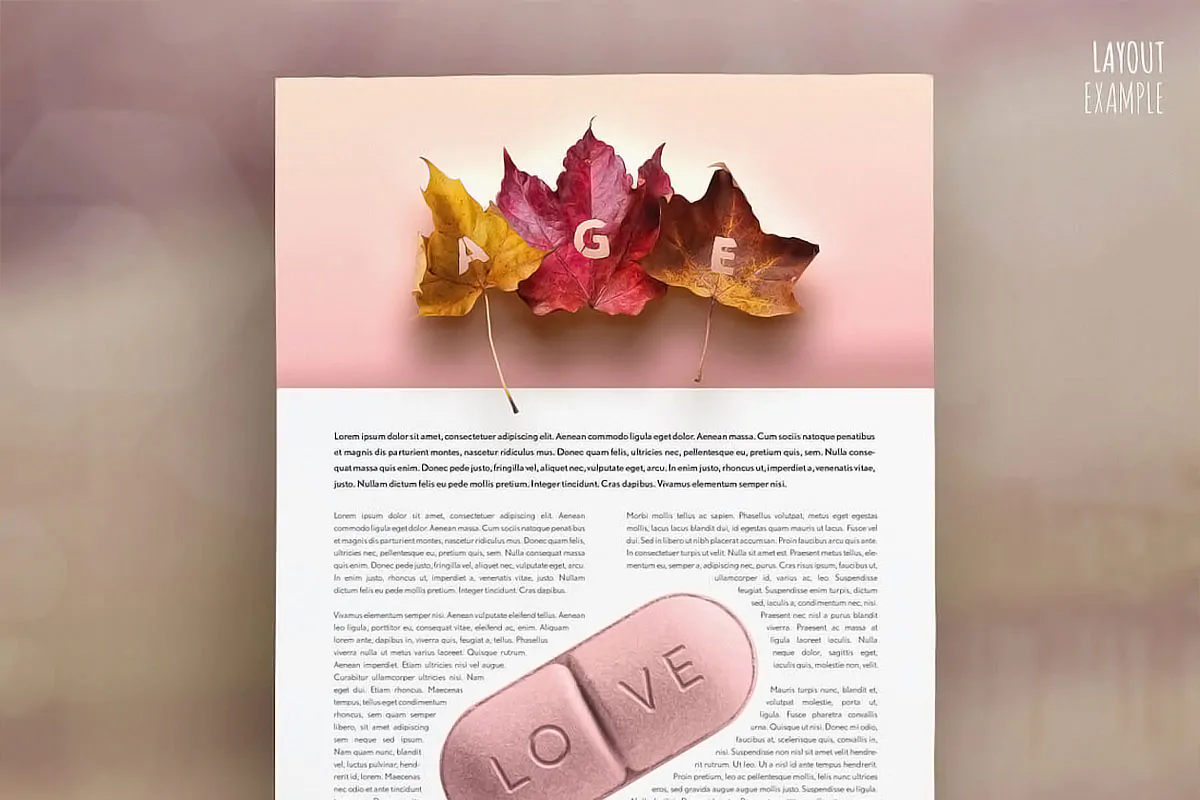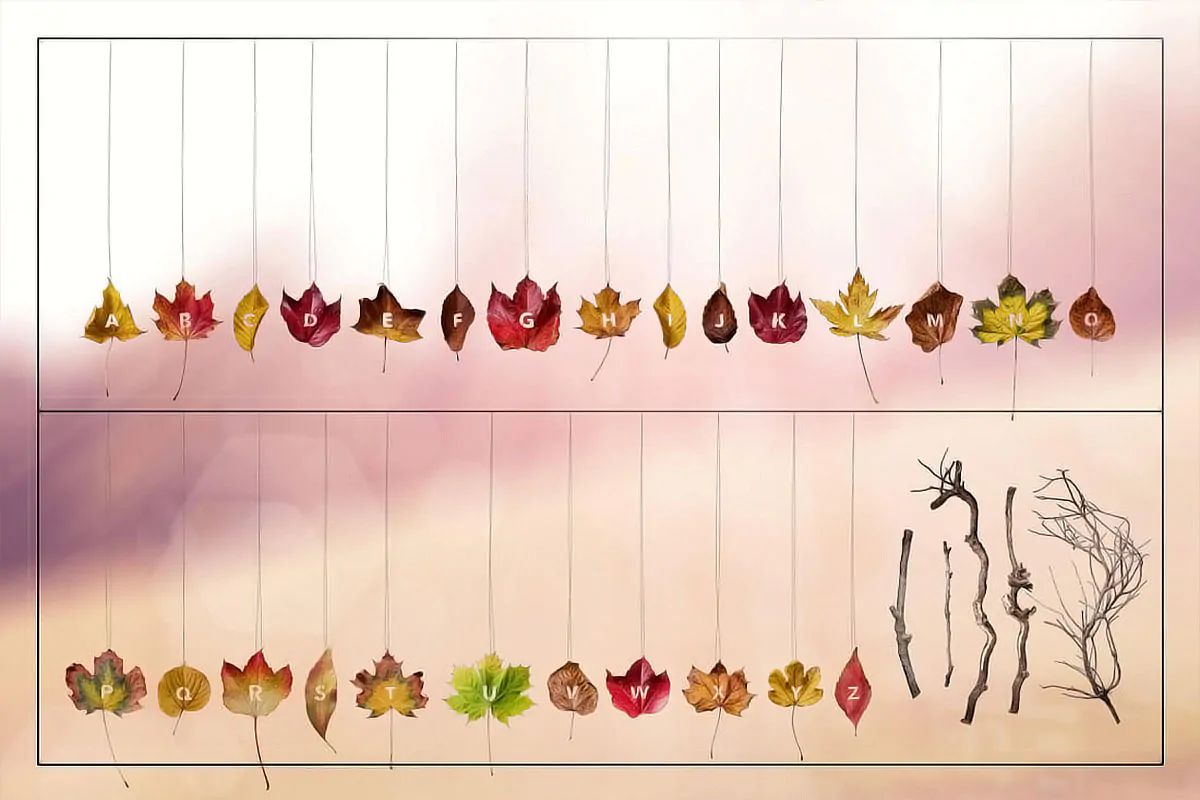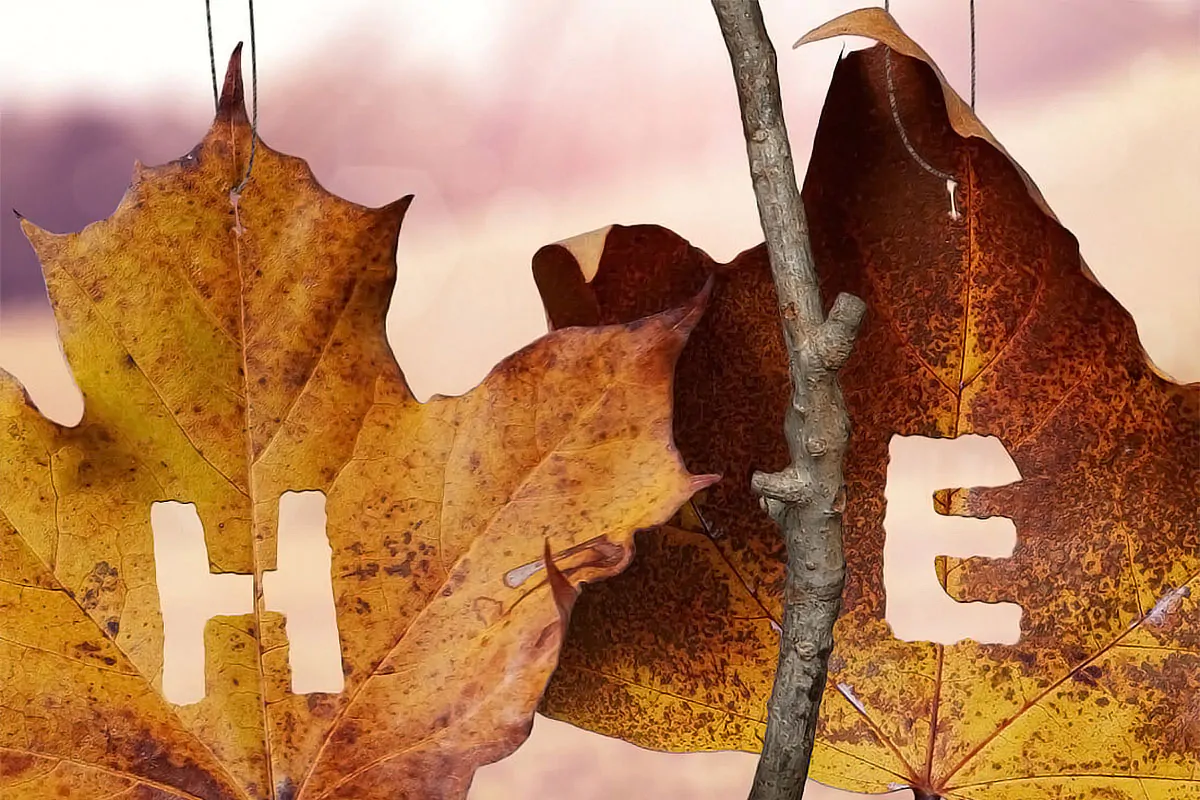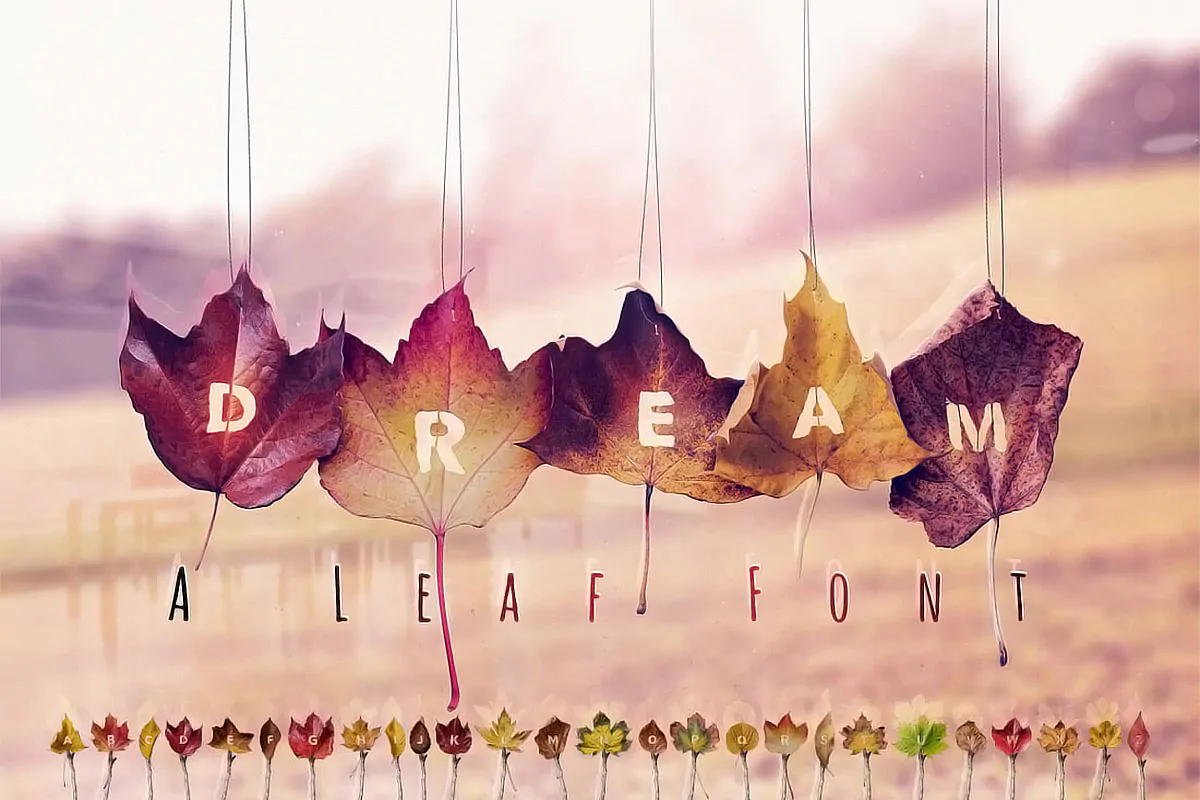
فونت برگی (PNG حروف پاییزی)
PNG حروف پاییزی
فونت برگی یا PNG حروف پاییزی مجموعهای فوق العاده زیبا از حروف انگلیسی است که با طرح برگهای پاییزی و به صورت ترنسپرنت آماده شدهاند و مناسب برای استفاده در طرحهای گرافیکی مختلف به خصوص طراحی انواع پوستر و تراکت میباشند.